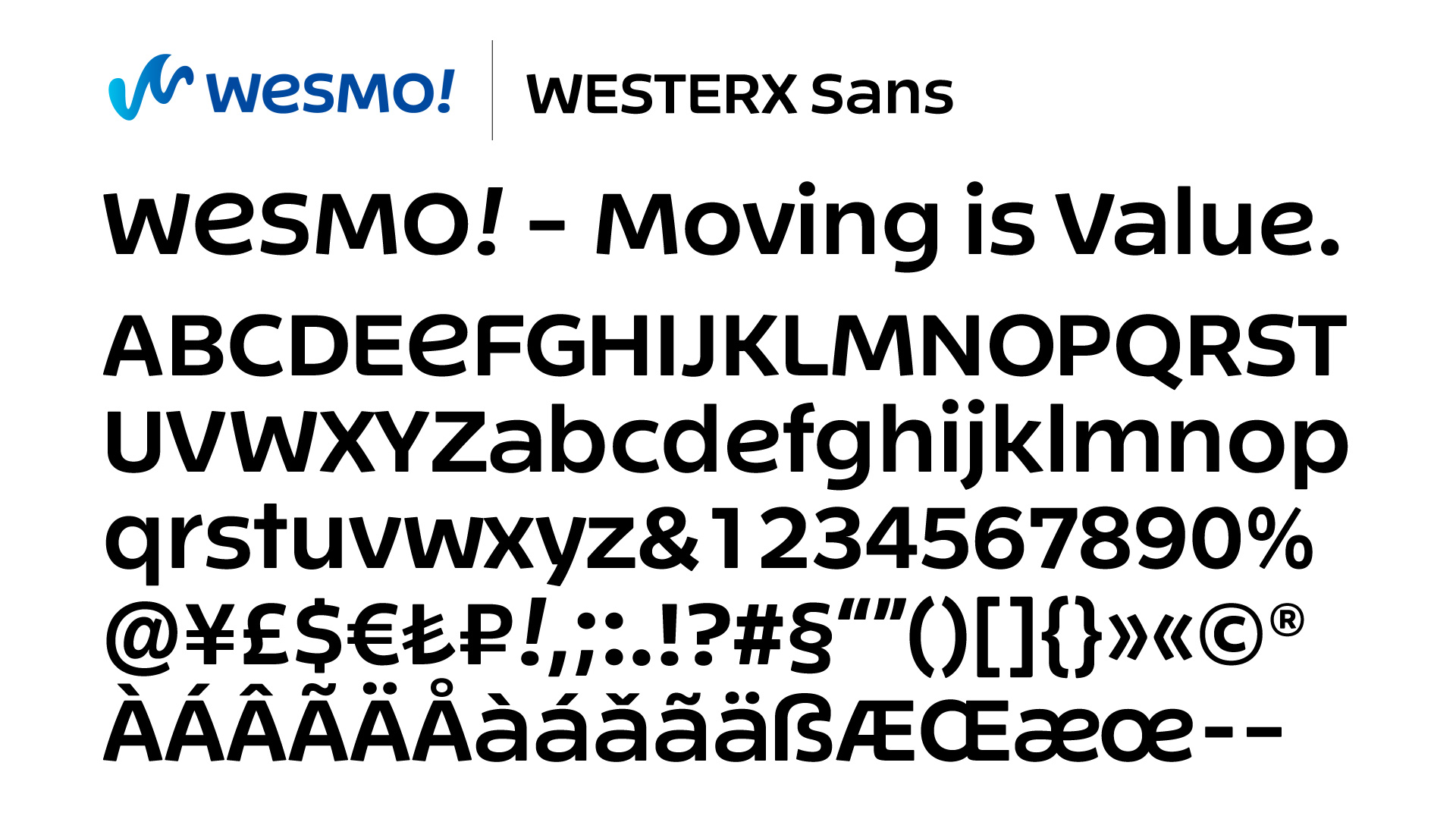
Monotype、JR西日本が提供する決済サービス Wesmo! オリジナルフォント「WESTERX Sans」を開発
米国Monotype Imaging Inc.の日本法人Monotype株式会社(東京都港区、以下Monotype)は、西日本旅客鉄道株式会社が提供する決済サービス「Wesmo!」のオリジナルフォントを開発しました。
Wesmo!(ウェスモ)は、西日本旅客鉄道株式会社(大阪府大阪市、以下JR西日本)が提供する新たな決済サービスです。動くことを価値にする——「Moving is Value.」をブランドコンセプトに掲げ、2025年5月28日(水)よりサービスを開始しました。
WESTERX Sansについて
欧文書体WESTERX Sans(ウェスターエックス・サンズ)は、Wesmo!のロゴタイプ、アプリ、広告などで幅広く使用するために開発されました。
デザインはMonotypeのクリエイティブ・タイプディレクター 小林章が担当。JR西日本 WESTER-X事業部、Wesmo!のサービスブランディングを手がけるセイタロウデザインの山崎晴太郎氏と共に、ブランドの声となる書体を制作しました。
制作にあたっては、ブランドコンセプト「Moving is Value.」に加え、「豊かさ」「敷居の低さ」「ユーモア」といったキーワードをもとに、複数の方向性から検討。あらゆるシーンで使用できる視認性や可読性を担保しながらも、動きとキャラクター性を大事にした、親しみやすい書体が完成しました。
Monotype クリエイティブ・タイプディレクター 小林章 コメント
制作を始めてお納めするまでの期間が約3ヶ月という異例の速さのプロジェクトでした。山崎さんのディレクションが的確だったこと、そしてJR西日本の皆さんからのフィードバックが素早かったことにも助けられました。お納めした後にいっしょに登壇した発表会で、JR西日本の方がさっそくスライドにWESTERX Sansを使ってくれて本当に楽しそうに話されていたのが印象に残っています。フォントがブランドの姿勢を伝える「声」になったということですよね。このコーポレートフォント制作に関わることができて、とても嬉しく思います。
書体の特徴
WESTERX Sansは、ブランドのパーソナリティーを伝える多様な表情を備えた欧文書体です。
最大の特徴は、外側にふくらみをもたせた丸みのあるフォルム。鋭角で硬い印象を与えがちな「M」や「W」も曲線で構成することで、柔らかく親しみやすい印象に仕上げました。また、ストロークの端にわずかな角度を加えることで、カジュアルさや躍動感を演出しています。
見出しでの使用を想定し、小文字は大きめに設計。大文字と組み合わせた際の凹凸を抑え、視覚的なまとまりを高めています。
決済サービスにおいて重要となる数字は、アルファベットとの調和を図りつつ、明快で安心感のあるデザインに。アプリを立ち上げるたびに、信頼性と親しみやすさが伝わることを目指しています。
さらに、Wesmo!のロゴタイプに使用されている「e」を大文字のバリエーションとして収録。微笑んでいるような表情を感じさせる、手書きの自然なストロークを採用しました。
今後の展開
WESTERX Sansは、2025年5月にリリースされたWesmo!のUI/UX、広告をはじめとしたブランドコミュニケーションで使用されています。